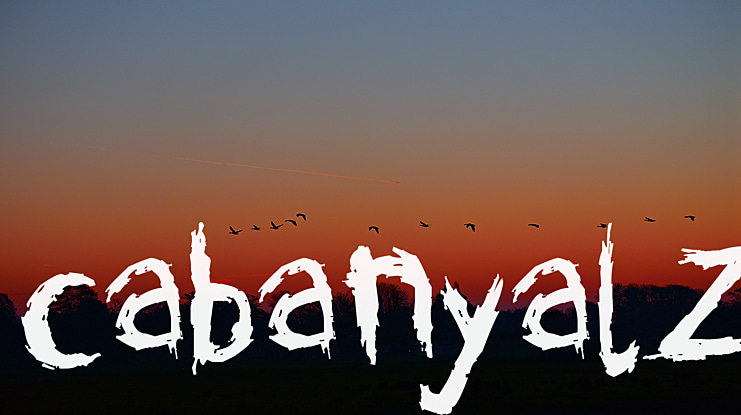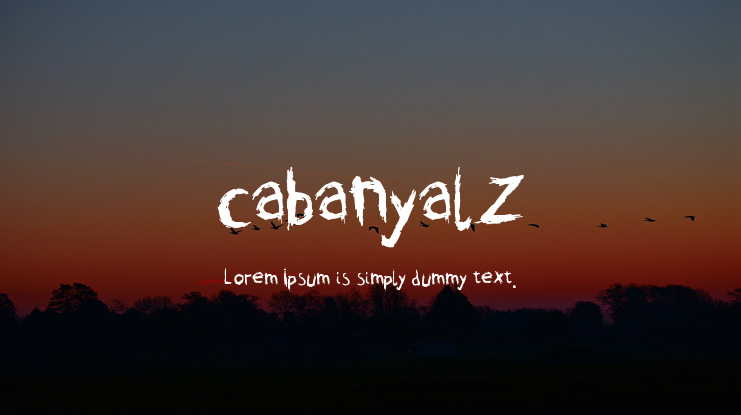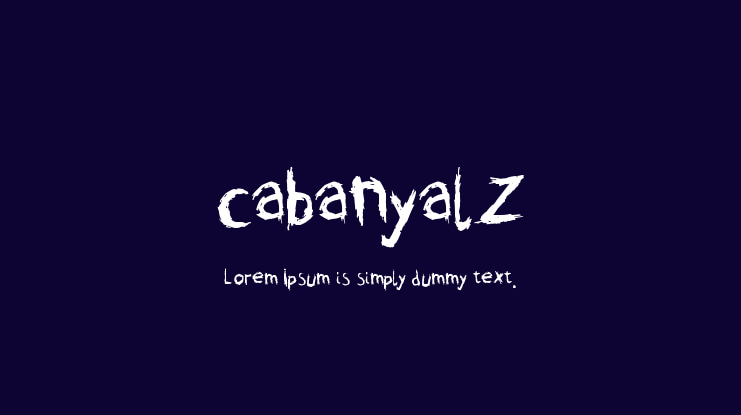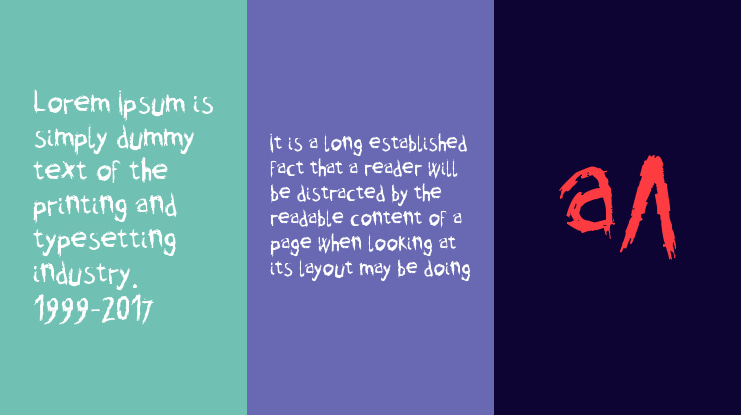
cabanyalZ Font
cabanyalZ-Jorgito Abuin
Tipografía creada para la webserie Cabanyal Z,la cual se autogestiona por la donación y venta de productos derivada de la misma.